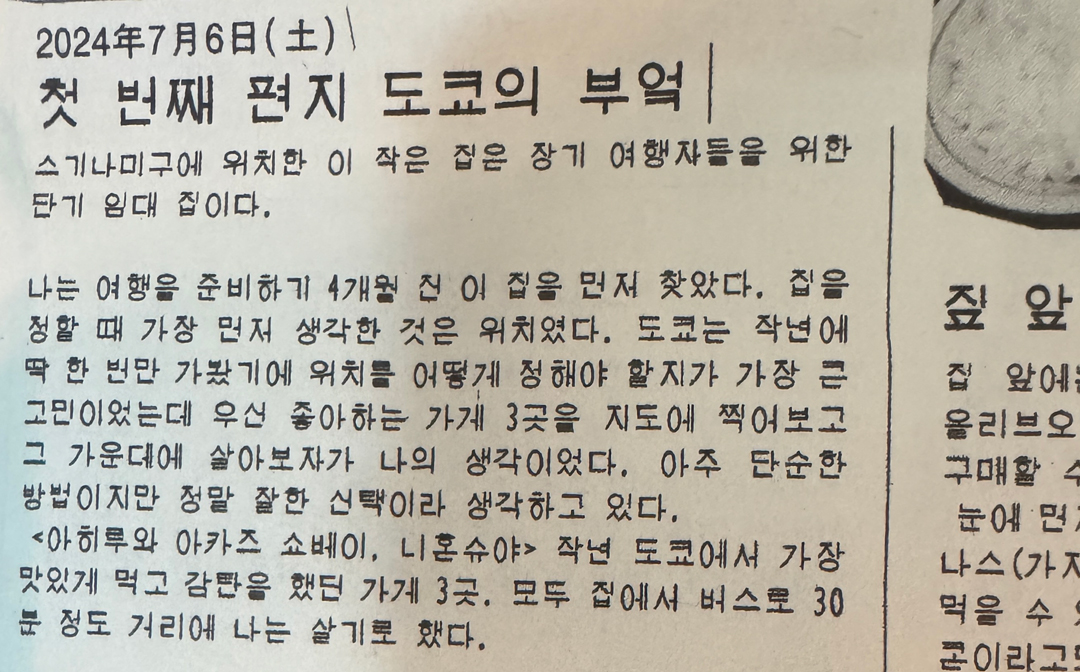
옛 한글 스타일 폰트
이 폰트 어떤건지 알 수 있을까요? 아래 사이트에서 발행한 인쇄물입니다. 분명 폰트인것 같은데 찾기가 어렵더라고요 ㅠㅠ https://ningenpaperpress.com/html/prints/life-cook-issue-2.html
뭔가 중국/일본회사에서 만든 시스템 기본 글꼴에 탑재되어있는 한글 느낌이 나는데... 그나마 느낌이 비슷한건 Arial Unicode MS 일것 같네요...